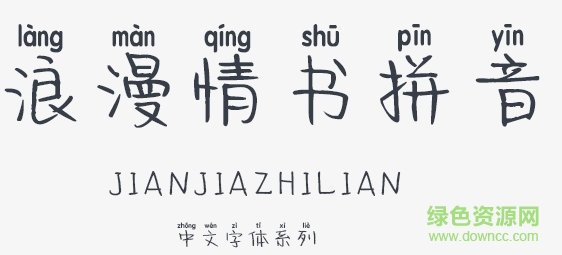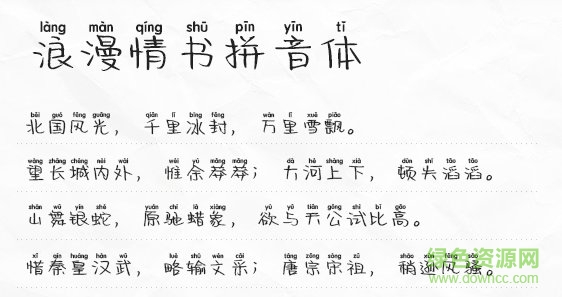
浪漫情書拼音字體是一款在浪漫情書字體上進(jìn)行美化修飾而來,增加了大家喜歡的拼音裝飾,讓文字閱讀更加明朗,綠色資源網(wǎng)獨(dú)家推薦!
浪漫情書拼音體字體飄逸灑脫,行筆流暢自然,字跡灑脫,具有濃厚的書法韻味,適合用于書籍、報(bào)刊、雜志的標(biāo)題和宣傳裝飾用字。
拼音字體是專門為漢語拼音制作的字體適合出版印刷和小學(xué)語文教學(xué)使用,按數(shù)字鍵就會(huì)出現(xiàn)字母帶音標(biāo),是一款非常實(shí)用的字體。